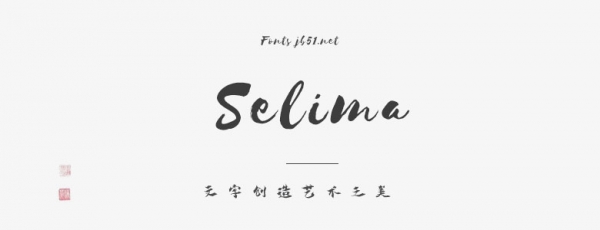
Selima的作者是來自印度尼西亞的Zam&Zoel,為了慶祝其網(wǎng)站Creativemarket成立一周年,向公眾提供特別的Selima字體。
Selima是一款具有油漆刷風(fēng)格的腳本字體,并支持字符的連接,不同字符會(huì)進(jìn)行自動(dòng)的連接以呈現(xiàn)更連貫的效果。